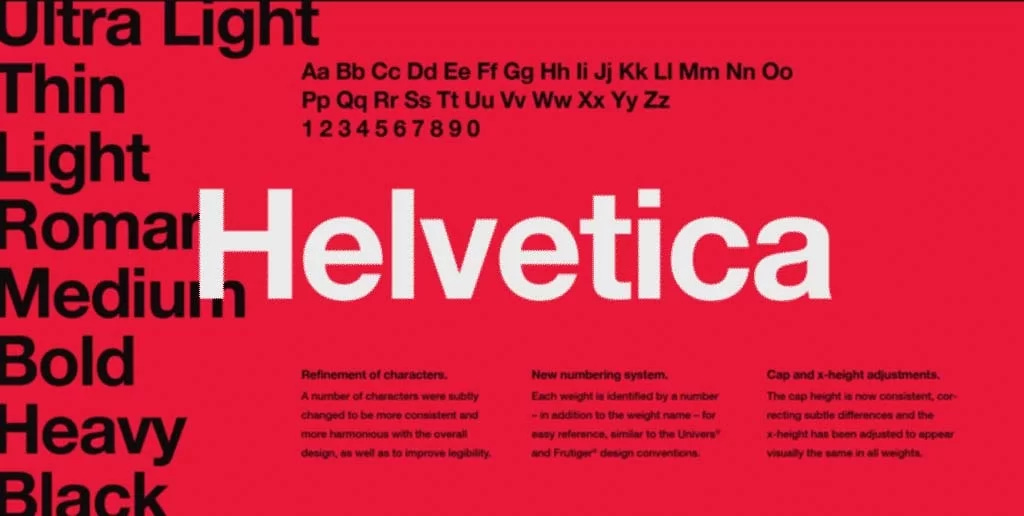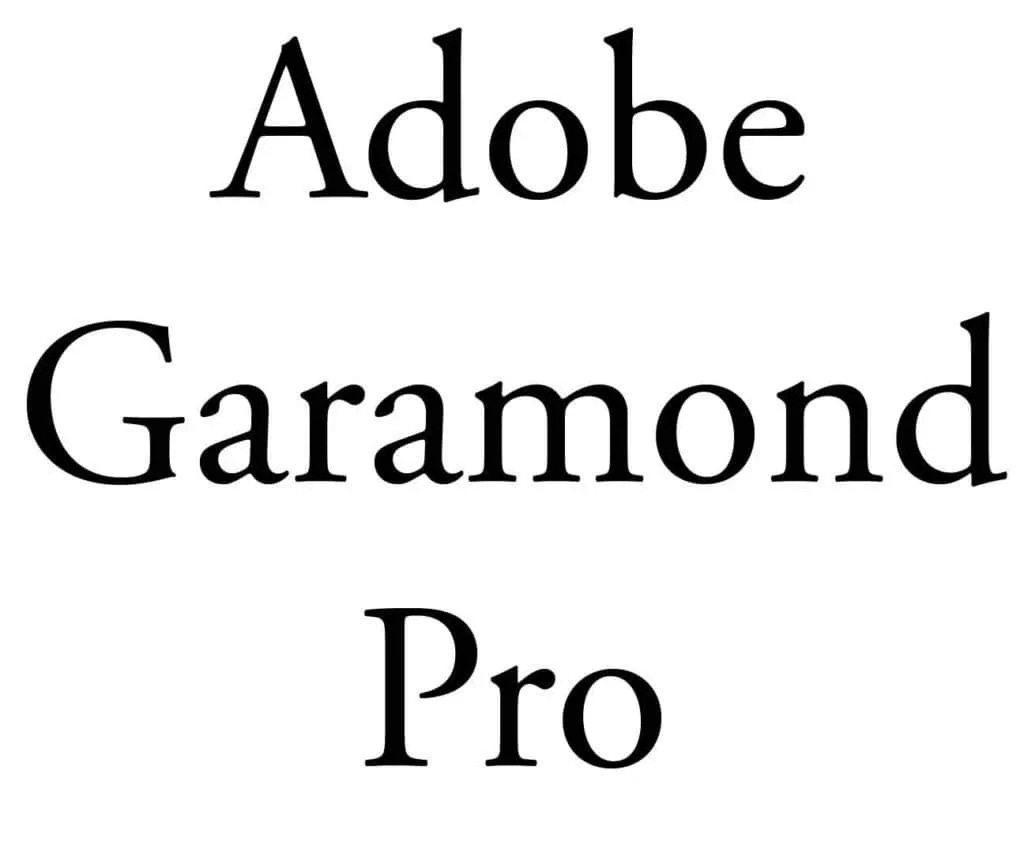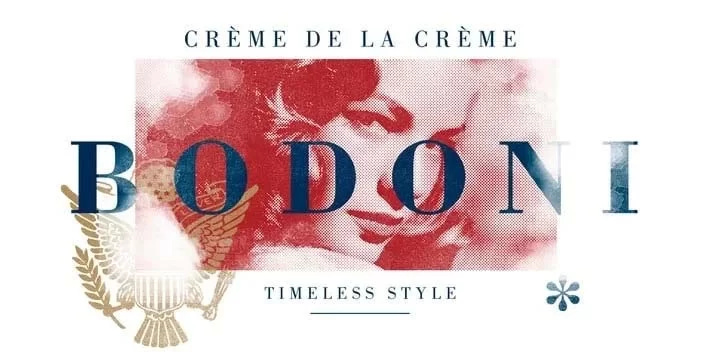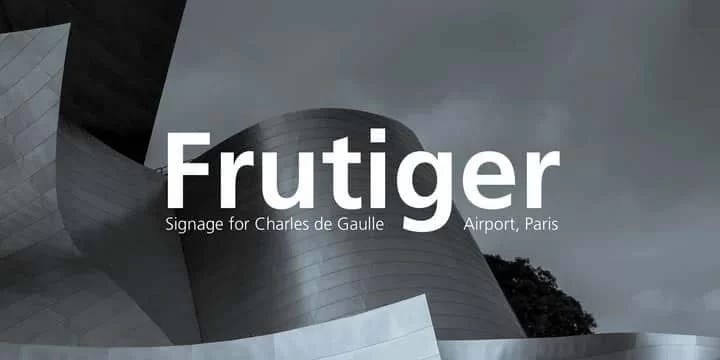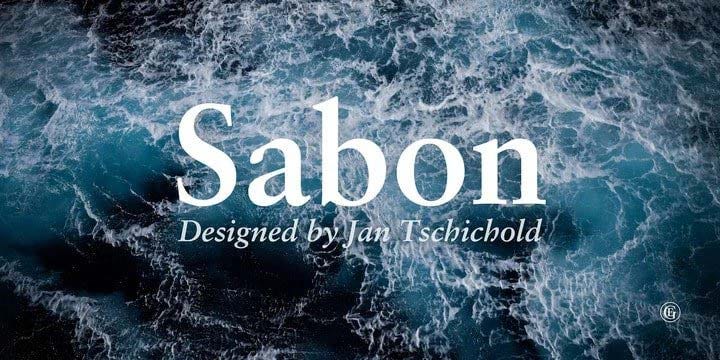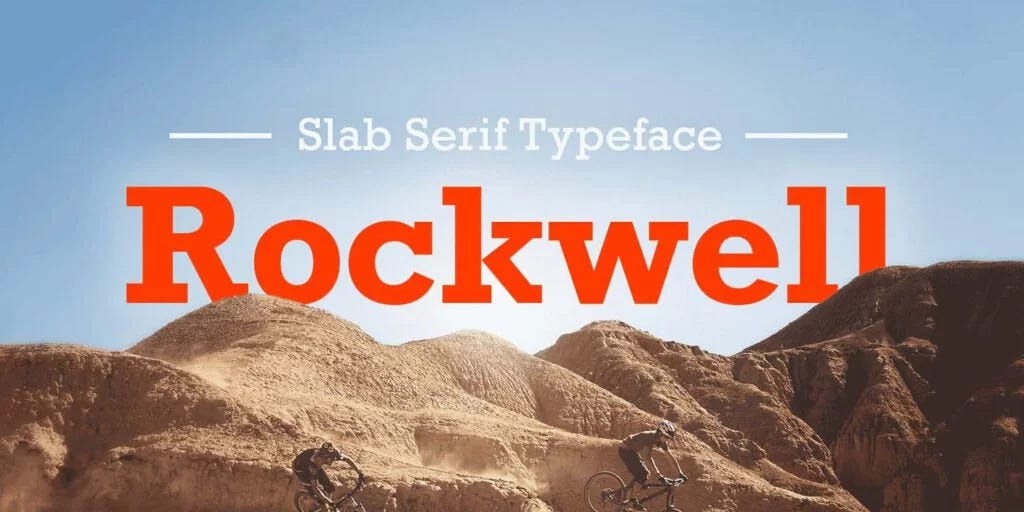
Profesyonel Grafikerler İçin En İyi Fontlar
Her tasarımcının koleksiyonunda sağlam bir profesyonel yazı tipi setine ihtiyacı vardır. Ancak piyasada bulunan binlerce yazı tipi arasından iyi olanları seçmek zor bir iş. Profesyonel tasarımcılar tarafından en sık kullanılan yazı tipleri şunlar.
Helvetica
Bodoni
Futura
Bickham Script Pro
Trajan
Proxima Nova
Garamond Pro
Frutiger
Sabon
Rockwell
Yazı Tipi Nasıl Seçilir?
Aslında yazı tipi seçimini etkileyen en önemli şey ne kadar uzun bir yazı yazdığınız ve amaçlarınız. Eğer bir kitap tasarlıyorsanız farklı, bir poster ya da bir web bannerı tasarlıyorsanız farklı karakterler kullanmalısınız.
Uzun yazılar yazıyorsanız göz yormayan düz hatlı fontlar seçmek normaldir. Tasarımı yalnızca font üzerinden planlamayın. Ayrıca en iyi tasarım örnekleri genelde düz, sade ve fontlar içerir.
Birden fazla yazı tipi kullanıyorsanız, yazı tiplerinin birbirinden çok farklı olduğundan emin olun. Fark belirgin değil ise bir hata gibi görünür. Ayrıca fontların kalınlık değerlerini ve kullanacağınız alternatif hallerini düşünün. Başlıkları daha kalın şekilde yazıp aynı font ile gövde metinleri daha ince yazabilirsiniz.
En İyi Yazı Tipleri
Bir sonraki grafik tasarım projeniz için profesyonel bir yazı tipi mi arıyorsunuz? Tasarımcılar için en iyi 10 profesyonel yazı karakteri listemize bakın.
Helvetica
Popüler bir font olan Helvetica, grafik tasarımda profesyoneller tarafından en çok kullanılan yazı tipidir. Çoğu tasarımcı yazı tipini övse de bazı tasarımcılar fontun çok dar aralıklı olduğunu düşünüyor.
Garamond Pro
Garamond’un birçok versiyonu olmasına rağmen, günümüzde en çok kullanılan hali 1989’da piyasaya sürülen Adobe Garamond Pro versiyonudur. Garamond, dergiler, ders kitapları, web siteleri ve uzun metin gövdeleri için çok kullanışlı bir yazı tipidir
Futura
Futura, genellikle büyük ekranlarda, logolarda, kurumsal yazı tiplerinde ve küçük metinlerin gerekli olduğu kitaplarda kullanılan bir yazı tipidir. Mükemmel daireler, üçgenler ve kareler gibi geometrik şekilleri temel alır. Futura verimlilik ve geleceğe dönük bir görünüme sahiptir.
Bodoni
Bodoni, başlıklar, dekoratif metinler ve logolar için harika bir yazı tipidir. Bodoni, düz ve dar bir alt yapıya sahiptir. Kalın ve ince vuruşlar onu çok estetik görünümlü bir yazı tipi yapan genel bir geometrik yapısı var.
Bickham Script Pro
Esas olarak resmi durumlarda kullanılan Bickham Script Pro, işini iyi yapan bir yazı tipidir. Bir başka harika alternatif de Sloop olacaktır.
Frutiger
Her karakterin hızlı ve kolay tanınmasını sağlayacak şekilde tasarlanmıştır. Bu farklılık, onu tabela ve dış mekan reklam çalışmaları için doğru bir alternatif olarak kılar ve genellikle Web 2.0 Logolarında kullanılır.
Sabon
Sabon, pürüzsüz doğası nedeniyle kitap metni ve zarif tasarımı için mükemmel bir yazı tipidir ve uzun süredir tipografların ve profesyonel tasarımcıların gözdesi olmuştur.
RockWell
Sağlam, düz kenarlıdır ve sert bir tavır sergiler. Çoğu profesyonel tasarımcının setinde var. Okunaklı ve anlaşılır bir font.
Proxima Nova
Proxima Nova yazı tipi, grafik tasarım projelerine çok minimal ve profesyonel bir görünüm kazandırabilen çok amaçlı modern bir fonttur.
Proxima Nova Extra Condensed, Proxima Nova ve Proxima Nova Condensed olmak üzere üç genişlik seçeneği vardır.
Ücretsiz Fontlar
Eğer yukarıdaki yazı karakterlerine ücretsiz font alternatifleri arıyorsanız. Google Fonts sitesine bakmalısınız. Gerçekten çok kaliteli ve profesyonel tasarımcılar için fontlar mevcut. En sevilen ve başarılı bulunan 5 ücretsiz fontu burada bulabilirsiniz.
Roboto
Google fontları arasında bulunan anlaşılabilir sade bir font. Yapısı Helvetica fontuna benziyor. Kullanılabilir seçenekleri de oldukça fazla. İnternet sitelerinde, reklam, afiş gibi tasarımlarda kullanmak için uygun bir font.
Besley
Bir başka ücretsiz yazı tipi Besley. Tırnaklı bir font arıyorsanız iyi bir alternatif olabilir. Özellikle italik kullanımı çok keyifli bir fonttur.
Allison
Biraz daha farklı bir yazı tipi mi arıyorsunuz? Eğlenceli, bir el yazısı gibi asimetrik ancak okunaklı bir font. Allison ücretsiz olarak sunulan keyifli bir yazı tipi.